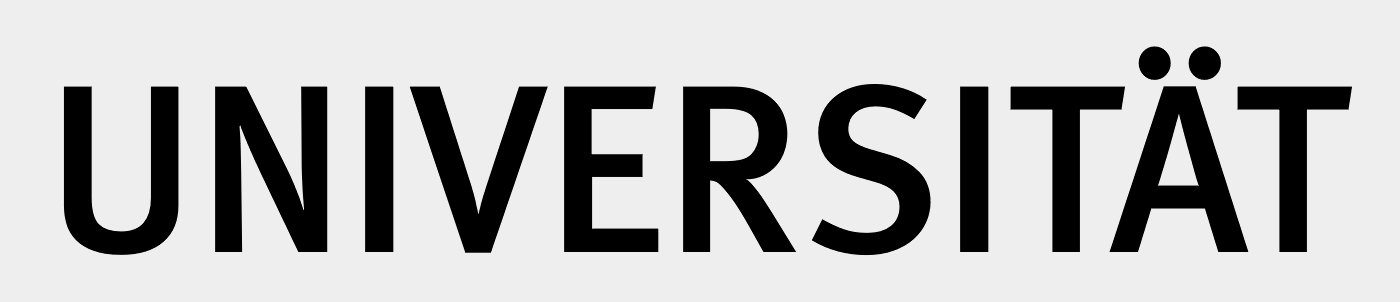
Welche Schriftart ist auf diesem Bild
ich suche die verwendete Schriftart auf diesem Bild. Diese ist sehr ähnlich zu Arial, jedoch sind bei Arial die Punkte bei Umlauten eckig und nicht rund wie auf diesem Bild. Die runden Punkten gefallen mir mehr als die Eckigen. Daher suche ich diese Schriftart.